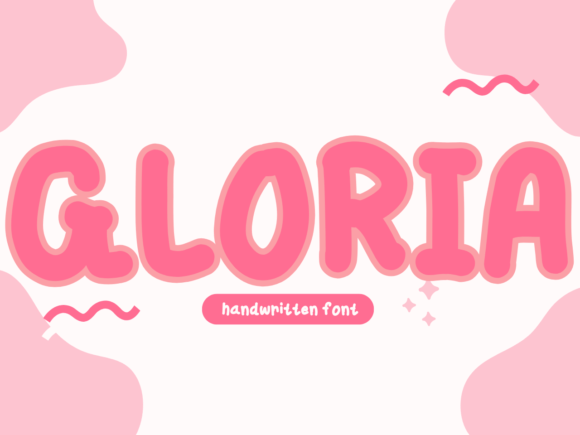
Gloria
Si vous recherchez des ressources de haute qualité comme Gloria, ce pack premium est un choix fantastique pour vos projets créatifs.
Conçu avec précision, Gloria offre des vecteurs nets, une typographie fluide et une licence commerciale pour une tranquillité d'esprit.